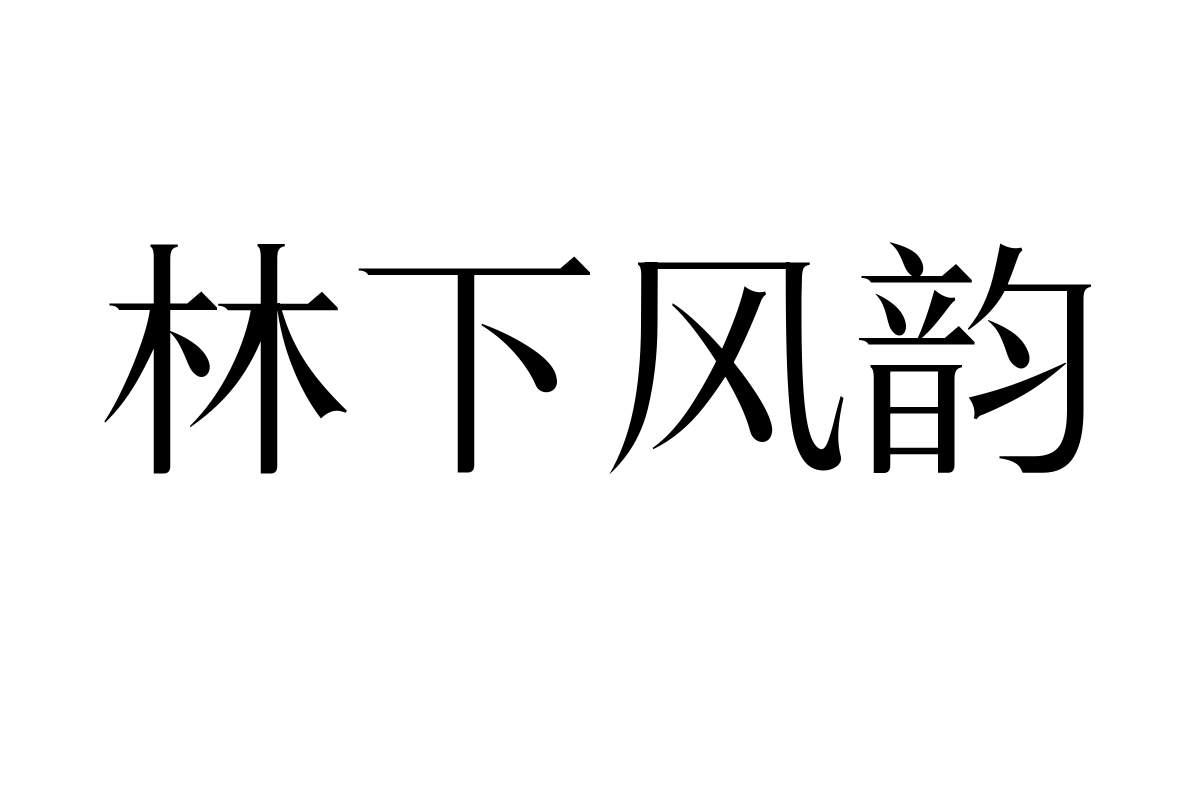
三极锦宋简体是一款由“三极”公司开发的中文字体,具有独特的风格和设计。这款字体采用了传统的书法艺术元素,结合了现代的简洁线条和结构,创造出一种新颖而优雅的视觉体验。
在三极锦宋简体中,每个字符都经过精心设计,以确保其清晰易读。字体中的笔画流畅自然,没有过多的装饰性细节,使得文字更加简洁明了。同时,这款字体还注重保持字形的稳定性和可读性,即使在不同大小和行距下也能保持良好的视觉效果。
除了美观大方之外,三极锦宋简体还具有较强的可扩展性和适应性。无论是用于印刷、广告还是网页设计,这款字体都能提供出色的效果。此外,它还支持多种语言版本,满足不同国家和地区的需求。
总之,三极锦宋简体是一款极具创意和实用性的中文字体,适合用于各种需要强调美感和易读性的场合。